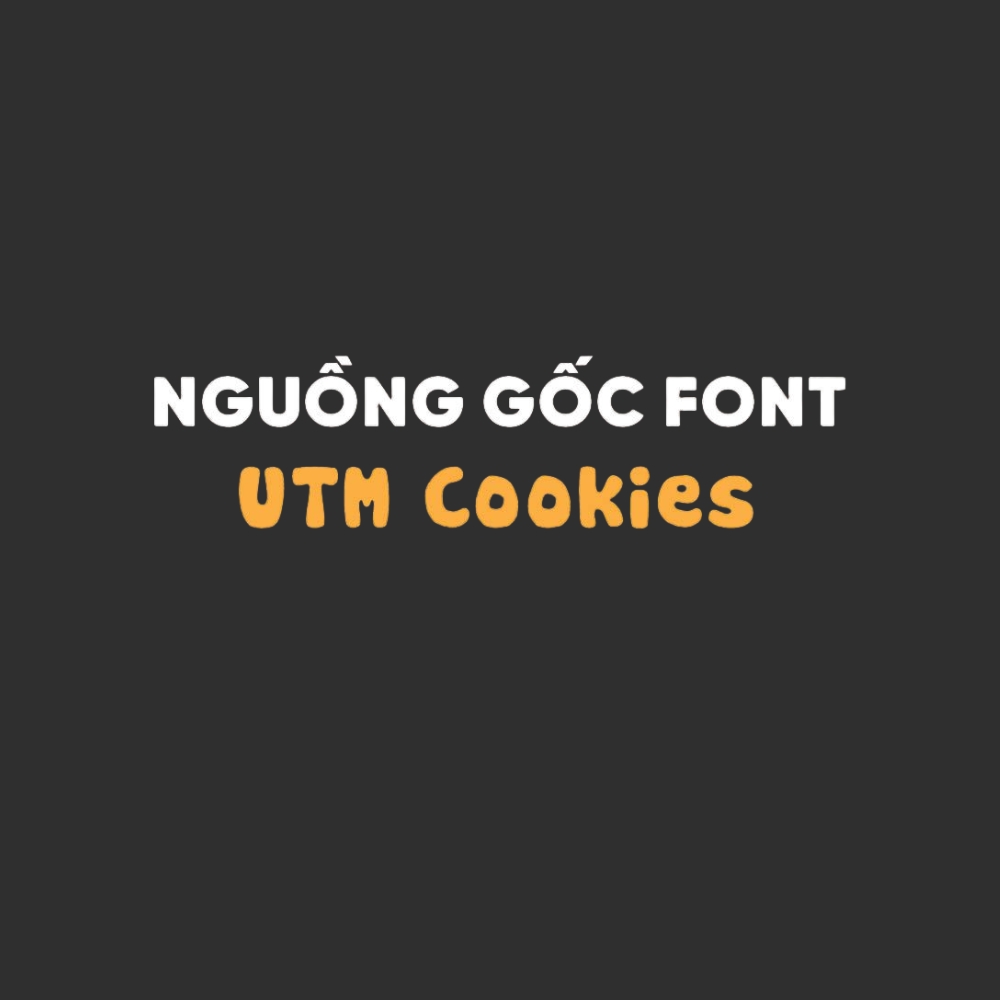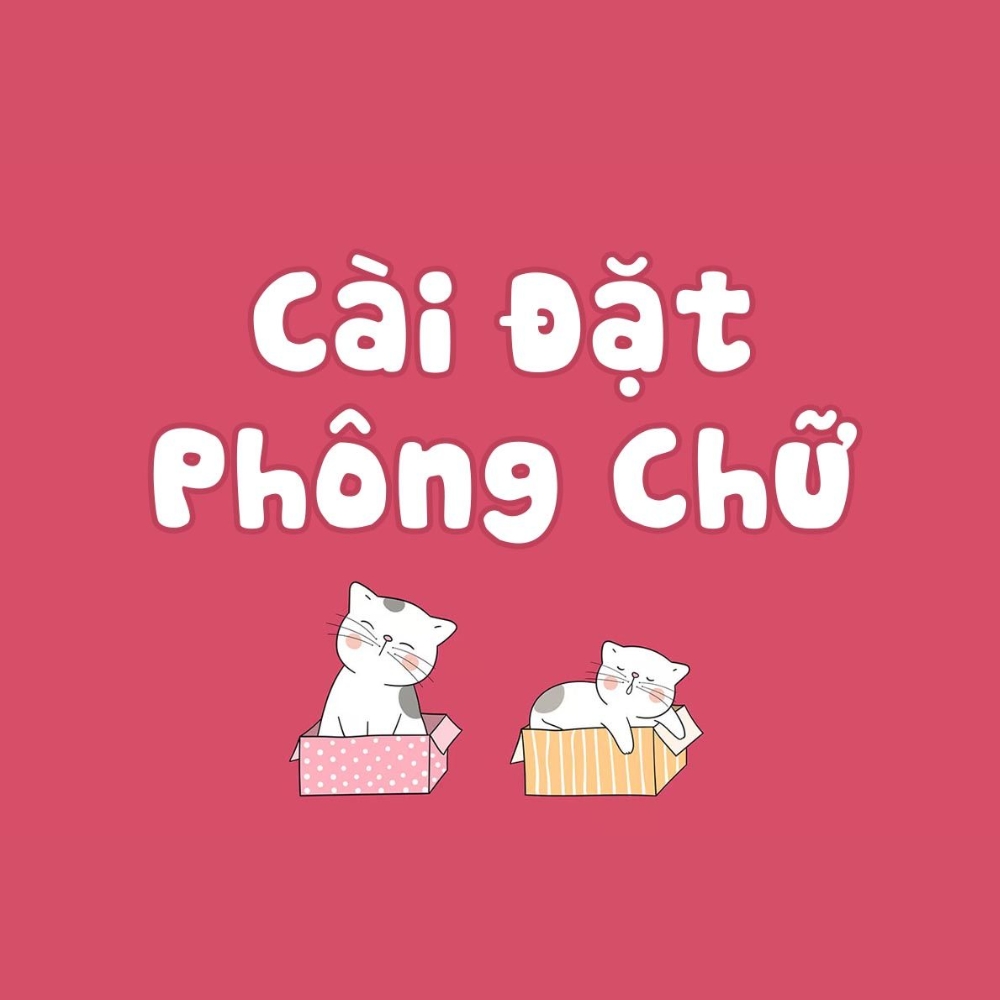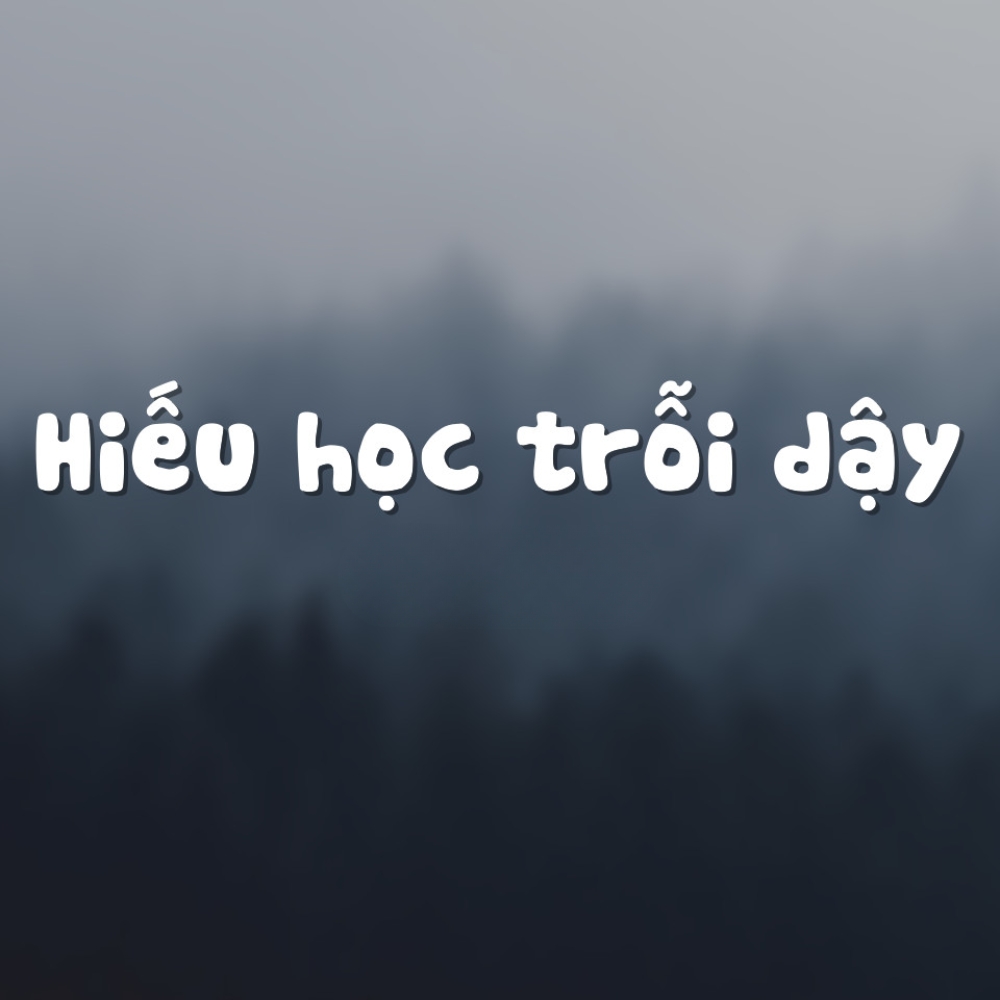
UTM Cookies việt hoá là font script viết tay có nét bút tự nhiên và đáng yêu, được dùng phổ biến trong thiết kế bao bì thực phẩm, thiệp và nội dung mạng xã hội tại Việt Nam nhờ bộ Việt hóa UTM đầy đủ dấu. Ở bài viết này, In Viva chia sẻ link tải font UTM Cookies việt hóa miễn phí và hướng dẫn dùng đúng bối cảnh nhé.
Font UTM Cookies Việt hóa là lựa chọn lý tưởng cho thiết kế mang phong cách viết tay tự nhiên, dễ thương và gần gũi. Trước khi tải, bạn nên hiểu rõ định dạng và khả năng hỗ trợ tiếng Việt để sử dụng đúng cách.
Đặc điểm của font UTM Cookies
- Nét bút tự nhiên, không hoàn hảo có chủ đích: Cookies mô phỏng nét viết tay bình thường — không quá trang trọng như thư pháp, không quá tùy tiện như scrawl. Điểm ngọt ngào nằm ở độ nghiêng nhất quán và sự biến thiên nhỏ trong độ dày nét.
- Phong cách casual và thân thiện: khác với các font script phức tạp, Cookies dễ đọc và gần gũi — cảm giác như được viết tay bởi người thật, không phải máy móc.
- Chỉ có Regular, không weight phụ: UTM Cookies là font đơn weight. Không thể làm đậm thêm bằng cách Bold trong phần mềm — thao tác đó tạo ra nét chữ giả, không đúng thiết kế gốc.
Ứng dụng của font UTM Cookies việt hóa trong thiết kế
Font UTM Cookies phù hợp với các thiết kế mang tính cá nhân, thủ công và sáng tạo như bao bì handmade, thiệp hoặc nội dung mạng xã hội.
- Bao bì thực phẩm handmade và bánh kẹo: UTM Cookies tạo ra cảm giác làm thủ công tại nhà — phù hợp với bao bì bánh, kẹo, jam, granola và các sản phẩm thực phẩm artisan muốn định vị handmade và cá nhân.
- Thiệp chúc mừng và stationery cá nhân: font thân thiện và tự nhiên phù hợp với thiệp sinh nhật, thiệp cảm ơn và các ấn phẩm mang tính cá nhân hơn là doanh nghiệp.
- Nội dung mạng xã hội và caption Instagram: overlay text với UTM Cookies trên ảnh sản phẩm tạo ra phong cách visual nhất quán cho trang thực phẩm, lifestyle và thương hiệu nhỏ.
- Label sản phẩm nhỏ và hang tag: ở cỡ vừa phải (12–18pt), Cookies vẫn đọc rõ và tạo ra cảm giác thủ công cho label sản phẩm, phù hợp với candle, soap, jam và sản phẩm gift set.
Lỗi thường gặp khi dùng font UTM Cookies
Khi sử dụng font UTM Cookies việt hóa, người dùng dễ gặp lỗi về bảng mã, hiển thị tiếng Việt hoặc dùng sai mục đích khiến thiết kế kém chuyên nghiệp.
- Dùng UTM Cookies cho văn bản pháp lý và thông tin bắt buộc trên bao bì. Font script thủ công không phù hợp cho thông tin thành phần, hạn sử dụng và nhà sản xuất trên nhãn thực phẩm — các phần này cần font sans-serif rõ ràng theo quy định pháp lý.
- Bold font trong phần mềm tạo ra nét chữ giả không đúng thiết kế. UTM Cookies không có bản Bold — bấm Bold trong Word hay Illustrator tạo ra nét chữ bị dày giả và mất đi sự tự nhiên của font. Thay vào đó, tăng cỡ chữ để tạo điểm nhấn.
UTM Cookies và Cookies gốc khác nhau như thế nào?
Cookies gốc chỉ có ký tự Latin cơ bản, không có dấu tiếng Việt. UTM Cookies là bản Việt hóa bổ sung ký tự tiếng Việt theo bảng mã TCVN3, dùng được cho văn bản tiếng Việt sau khi cài bộ gõ phù hợp.